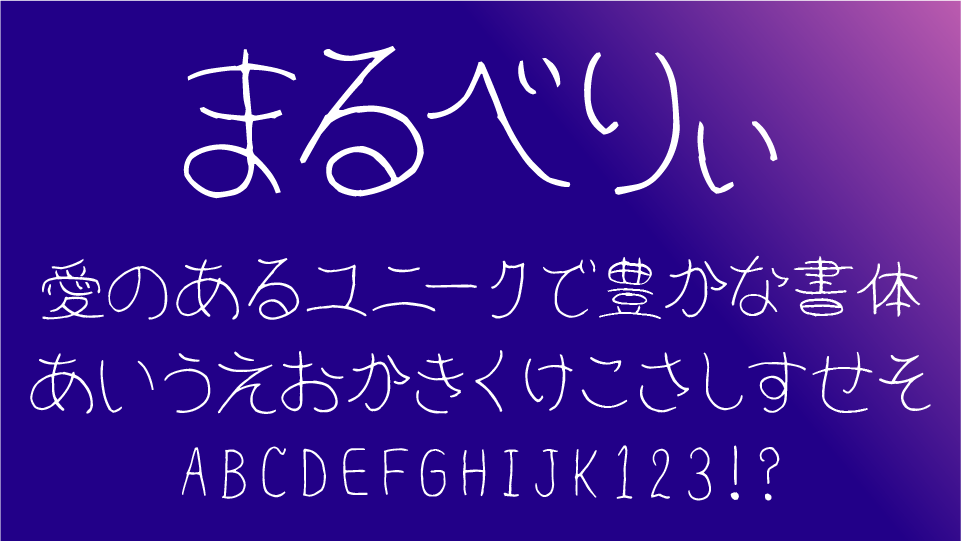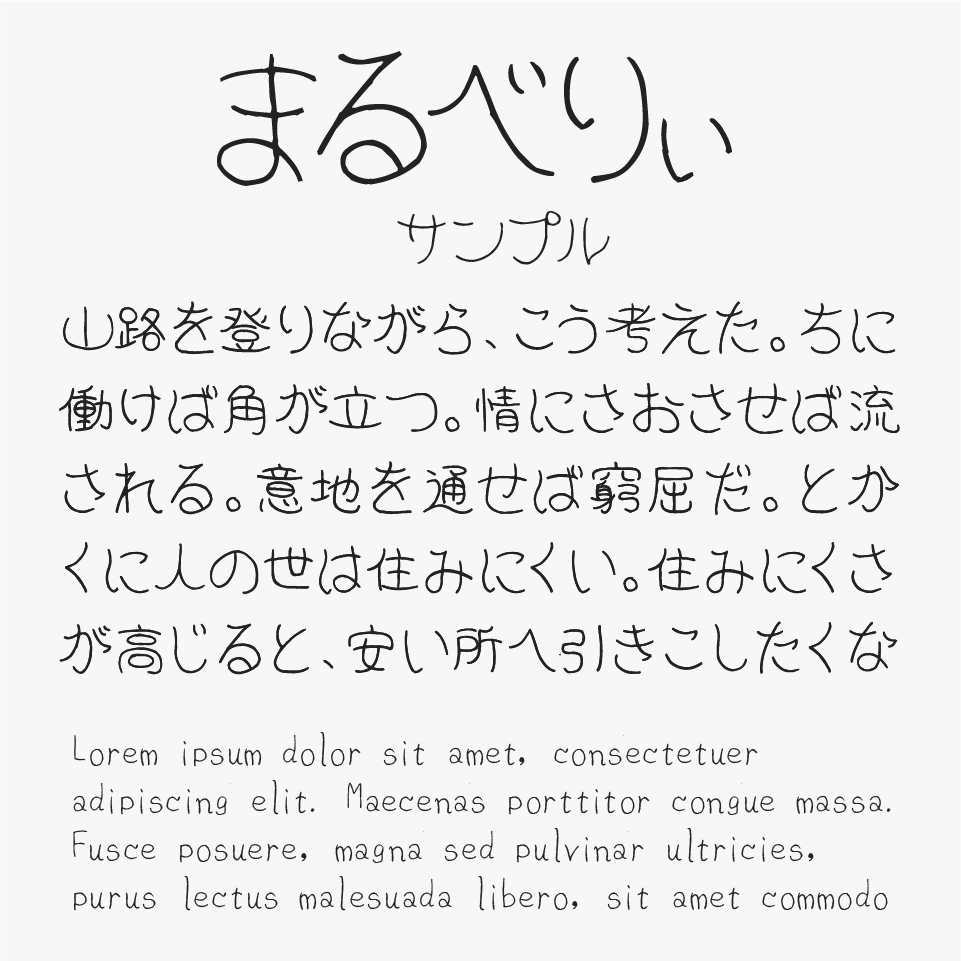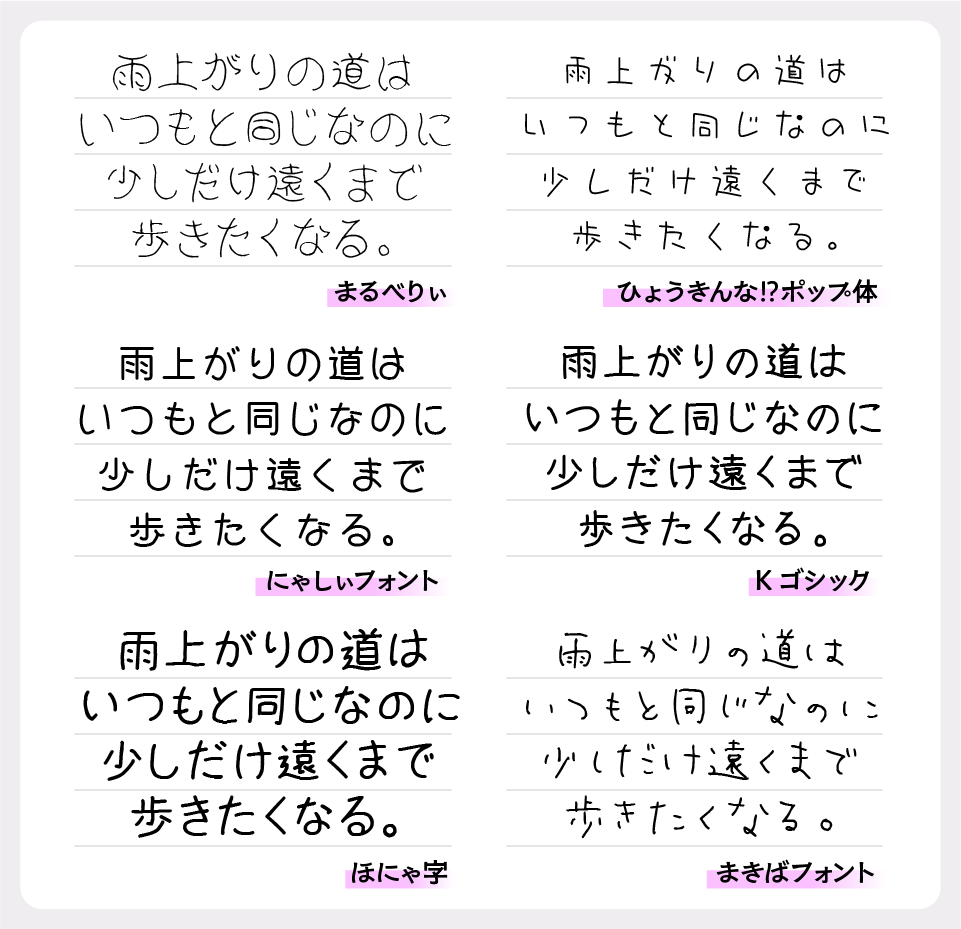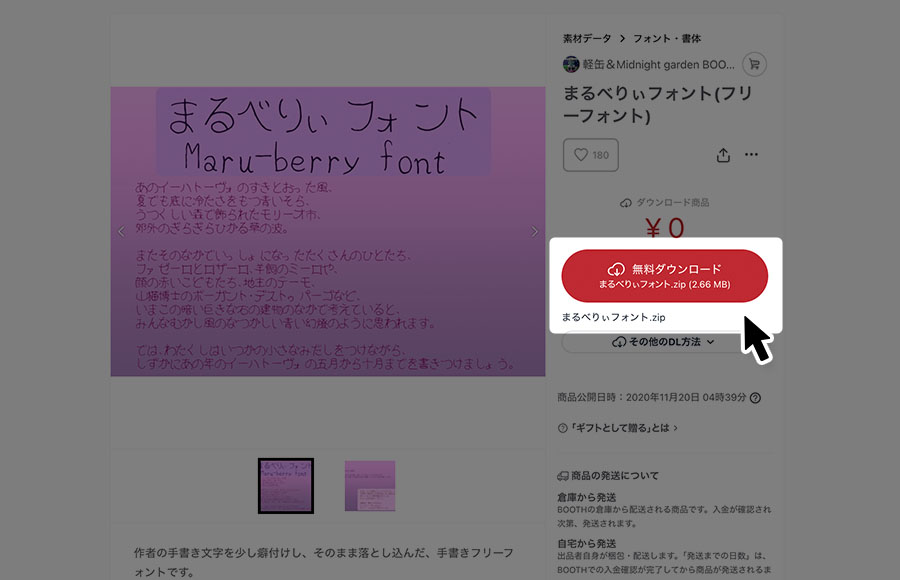
まるべりぃ
まるべりいフォントは、細めの手書き線で描かれたような繊細さと、ゆるやかで丸みのある可愛らしい手書きフォントです。
全体的に丸みを帯びたやさしいフォルムを持ちながら、どこか気の抜けたようなラフさがあり、親しみやすく素朴な雰囲気を生み出しています。作り込みすぎないナチュラルな表情が心地よく、手書きならではの温かみを感じられるフォントです。
やわらかく気軽な空気感を演出しやすく、SNS投稿やブログアイキャッチ、手紙風デザイン、雑貨デザイン、ナチュラル系のバナー制作などにぴったりなフォントです。親近感のある表現が得意なため、日常感や素朴さを大切にしたいデザインで活躍するフォントです。
まるべりぃフォントを、ほかの丸みのある可愛らしいフォントと比較してみると、ふんわりとした優しいフォルムによって、見ているだけで安心感のある柔らかな印象のある手書きフォントとなっています。
比較フォントは、「ひょうきんなポップ体」「にゃしぃフォント」「Kゴシック」「ほにゃ字」「まきばフォント」を使用していますが、どれも特徴的な明朝体フォントなので、ぜひあわせてチェックしてみてください。